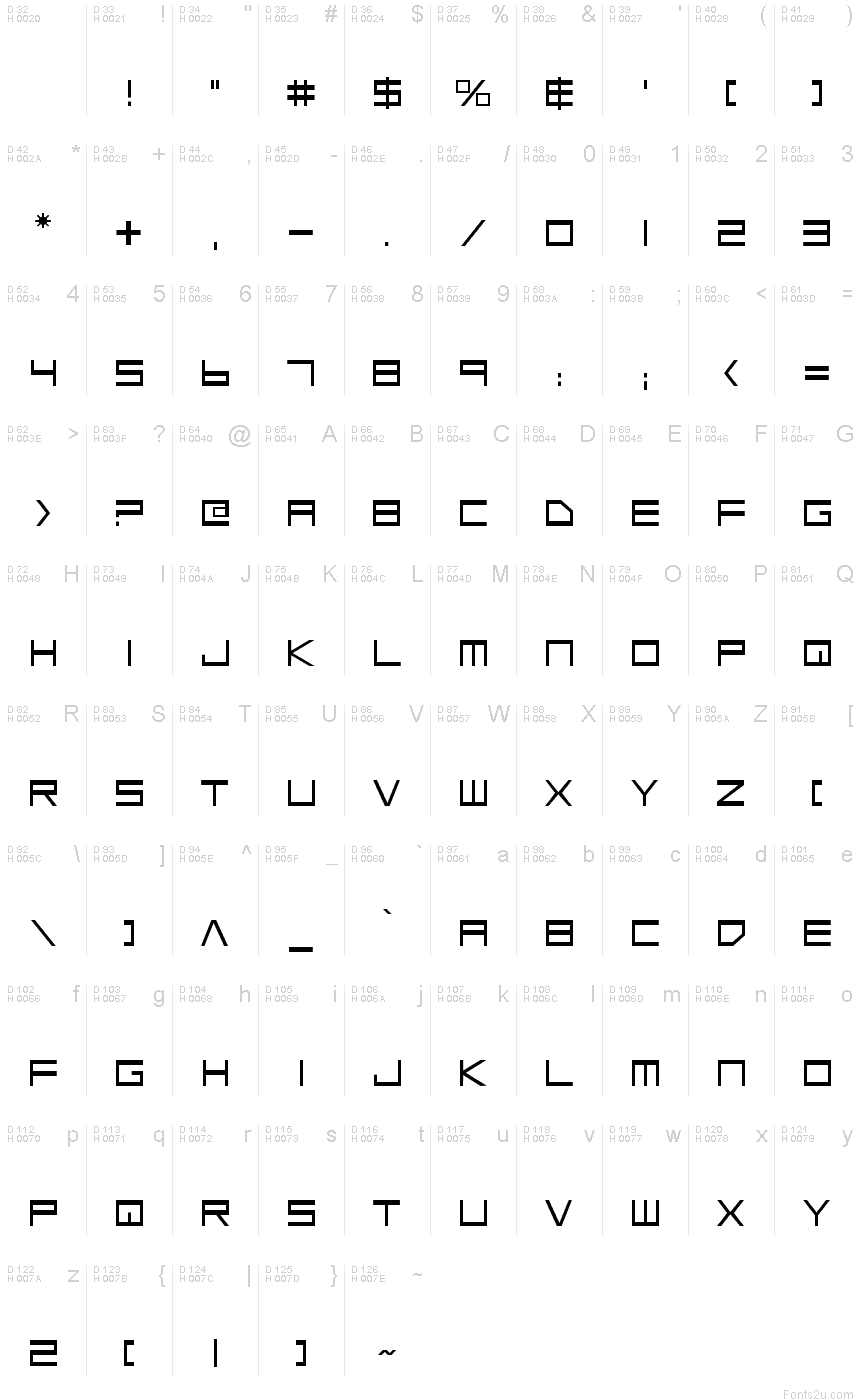
Low Gun Screen di Iconian Fonts è un font display techno gratuito dal look modulare e deciso, che richiama l'estetica delle console arcade e dei pannelli di controllo sci-fi. Le lettere sono composte da angoli retti massicci e aperture quadrate, con intagli affilati e giunzioni a gradino che rendono la geometria vivace invece che smussata.
È la soluzione perfetta per loghi di videogiochi, titoli, poster, grafiche per streamer e packaging futuristici, dove le parole brevi richiedono una voce elettronica rigida. Trattandosi di un font gratuito, è ideale anche per copertine e branding di interfacce, specialmente quando si cercano scritte compatte dall'aspetto meccanico e non troppo levigato.
Low Gun Screen